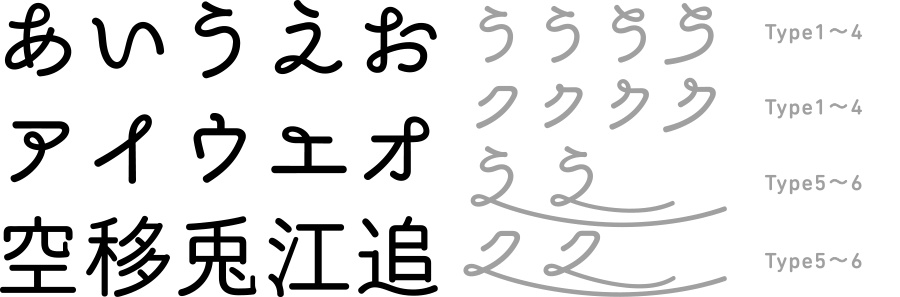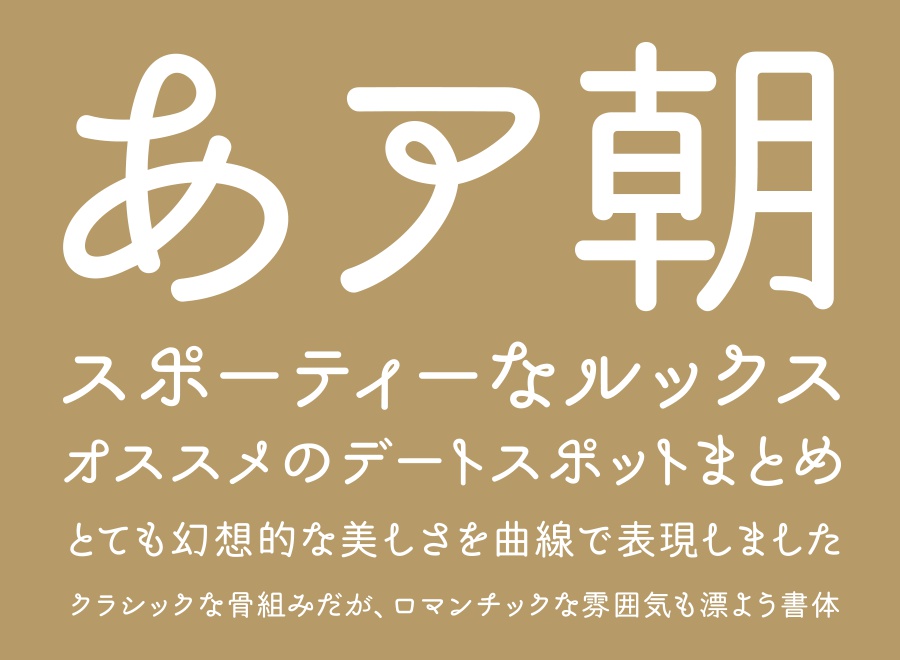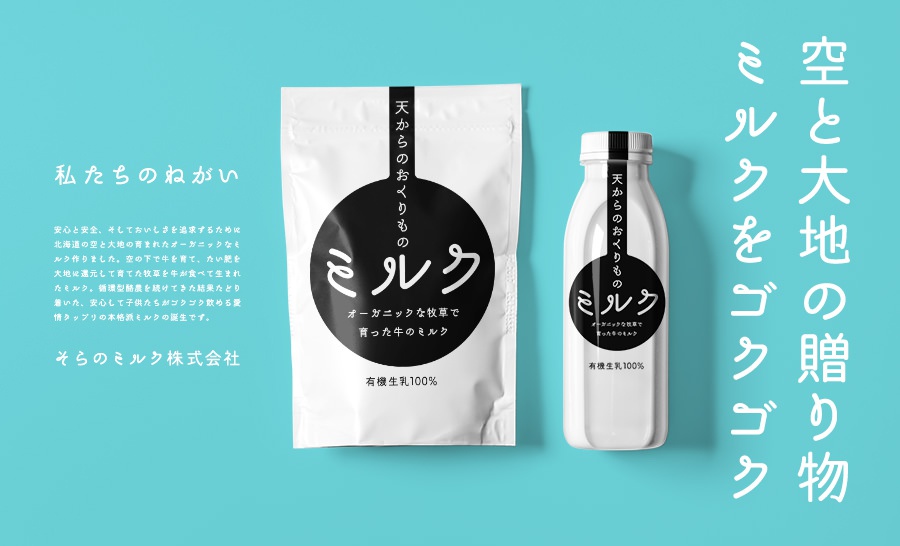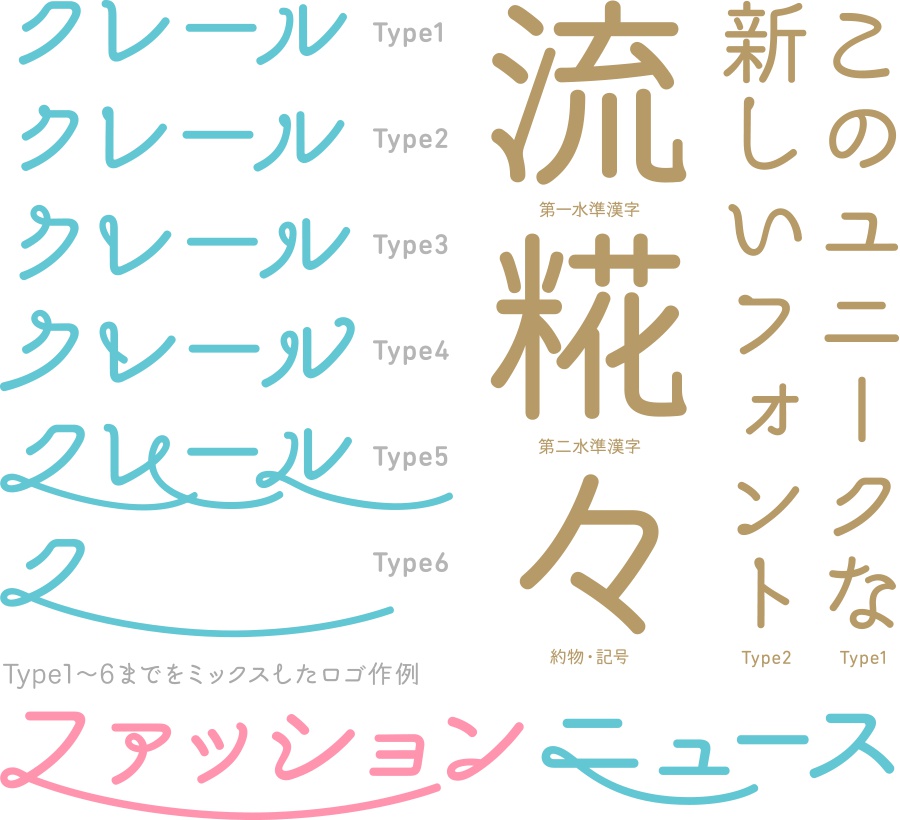
あさご本丸ゴシック - 7フォントSET
あさご本丸ゴシック 竹田城をイメージした優美な丸ゴシック体フォント 通称天空の城〜竹田城のある、朝来市をイメージした丸ゴシック体です。山城の雲海に浮かぶような幻想的な美しさを流れるような曲線で表現しました。のびのびとした毛筆のような流れが、優美な世界観とやさしい雰囲気を作り出します。 特典としてクルクルとしたカールの形状の度合いが異なる6種類のフォントを追加収録。シンプルなType1、先端の個性的なType2、遊び心のあるType3、伸びやかで見出しに向きのType4、ロゴの一部に使えそうなType5、Type5の倍の横幅のType6、どれも大活躍しそうな書体です。またOpenTypeの異体字機能が使える場合は「あさご本丸ゴシックR」1書体でType1〜 Type5の字形が切り替えられます。 収録フォント(7書体) あさご本丸ゴシック(レギュラー)、あさご本丸ゴシックType1〜Type6(6書体) 動作環境 Mac:システム/OS X対応(10.x)〜最新のOS X Windows:OS/日本語版Windows2000、XP、VISTA、Windows7〜11以降 フォント形式:OpenTypeフォント、TrueTypeフォント 収録文字数について 収録文字数4,072文字(第一水準2965文字+第二水準460文字+ひらがな.カタカナ.約物.記号.アルファベット等647文字) 安心して使えるロイヤリティフリーの書体 あらゆる商用・デザイン用途(印刷物・ゲーム・アプリ・映像・動画・ロゴ・同人作品)に使用できる、商用申請の必要のないロイヤリティフリーの書体になります。文字の加工・変形も可能です。ご安心ください。